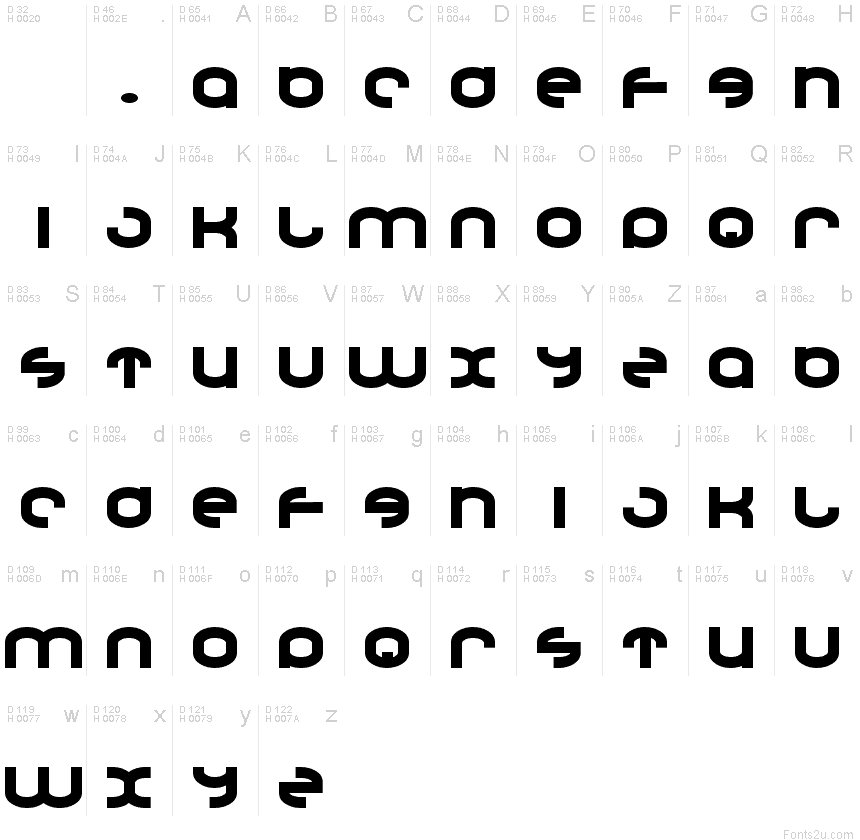
Dronecat di Claes Kallarsson è un font sans serif gratuito dallo stile futuristico, che sembra tagliato in acrilico lucido e smussato alla fresatrice. Le sue forme tozze e monolinea, i contatori squadrati e le curve strette creano un ritmo tecnico, quasi robotico, che risulta comunque amichevole e accessibile. Le lettere si incastrano in un flusso fluido e continuo, conferendo ai loghi una silhouette audace e unificata che cattura subito l'attenzione.
Con Dronecat, i titoli sembrano etichette di un'interfaccia di un sistema operativo del prossimo futuro: puliti, sicuri e inconfondibili. Questo font gratuito brilla nei loghi e-sport, nei poster di fantascienza, nel branding di startup tecnologiche, nel packaging di gadget, nelle schermate di avvio delle app e nei titoli di eventi di grande impatto. Per i testi più lunghi, abbina Dronecat a un semplice font sans serif in dimensioni minori per mantenere la leggibilità, lasciando che Dronecat gestisca i momenti di massimo impatto.